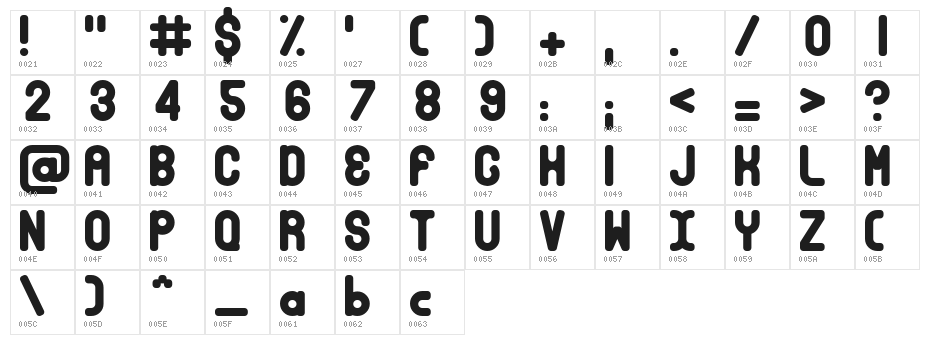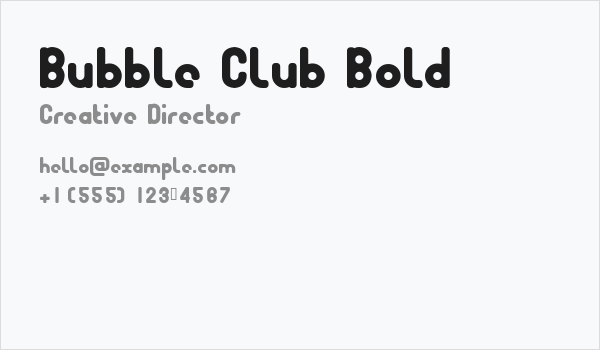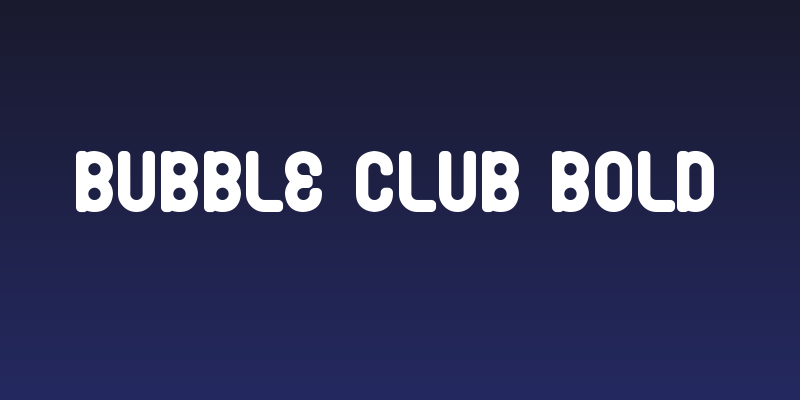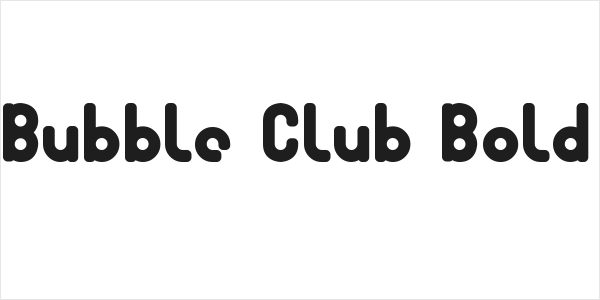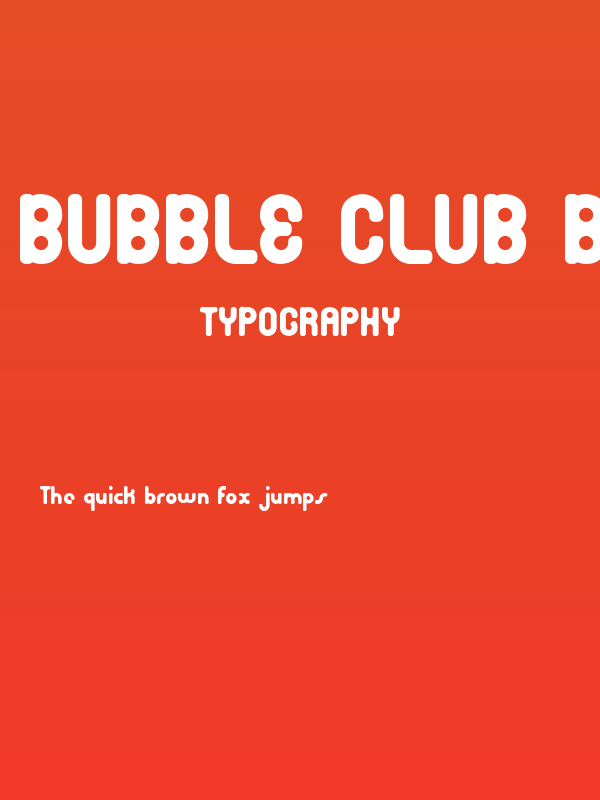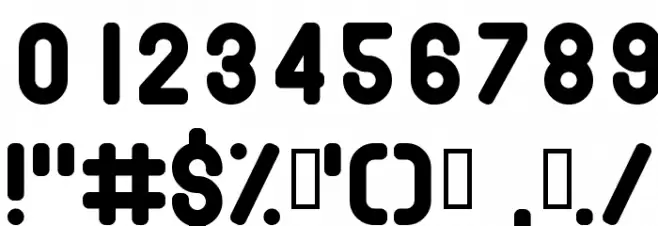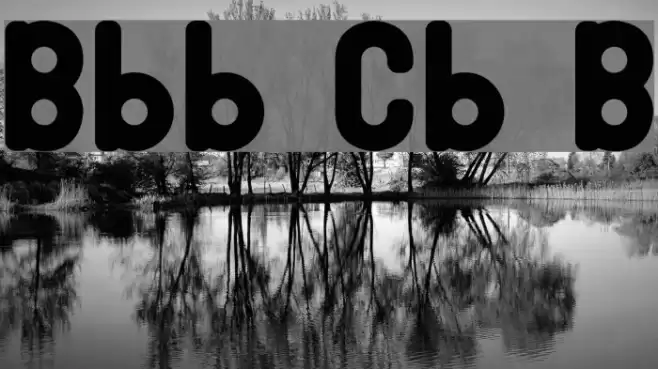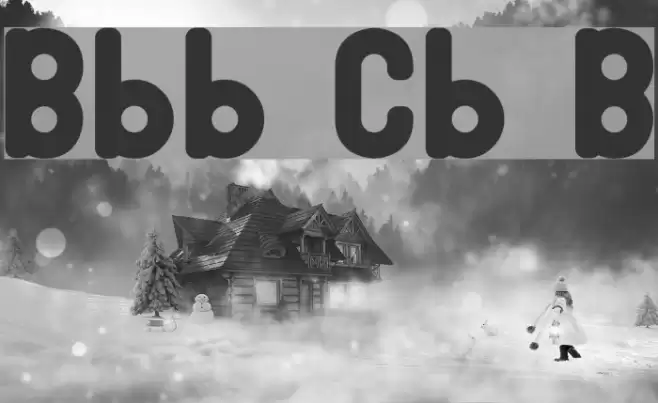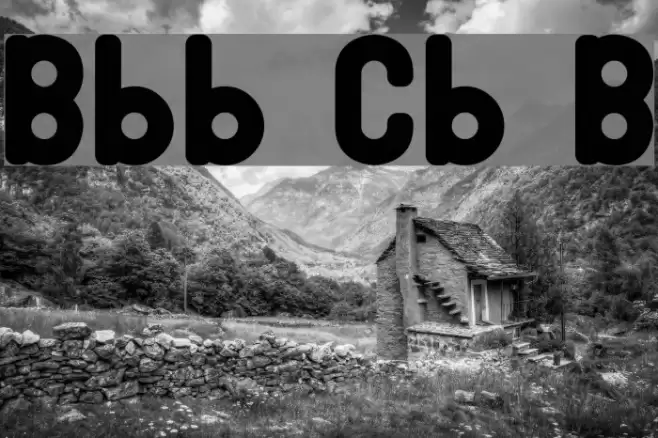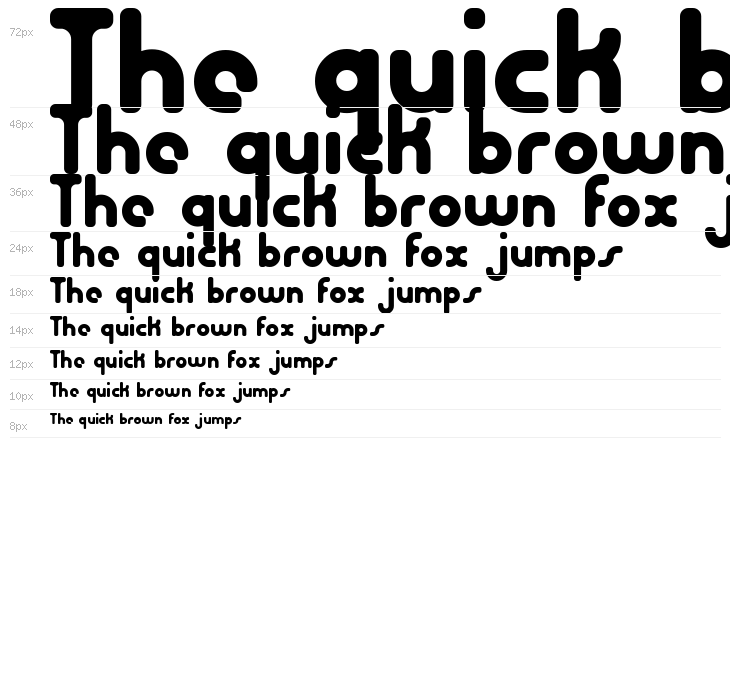
Bubble Club Bold Font
| Estilo general | Playful, Fun, Whimsical |
| Proyectos propuestos | Perfect for children's books, playful branding, party invitations, and any project that requires a fun and approachable aesthetic. |